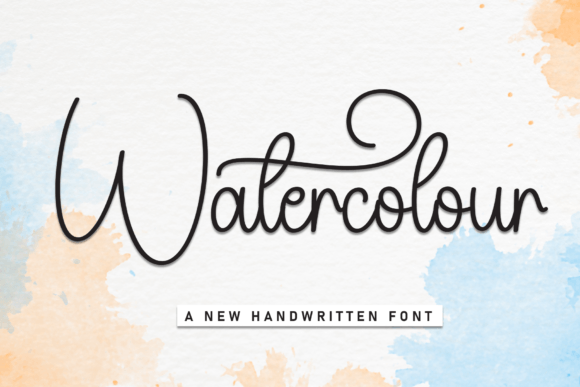
Watercolour
إذا كنت تبحث عن أصول عالية الجودة مثل Watercolour، فإن هذه الحزمة المميزة هي خيار رائع لمشاريعك الإبداعية.
سواء كنت تقوم بإنشاء منتجات الطباعة عند الطلب أو دعوات الزفاف أو رسومات وسائل التواصل الاجتماعي، فإن Watercolour هو الخيار المثالي.